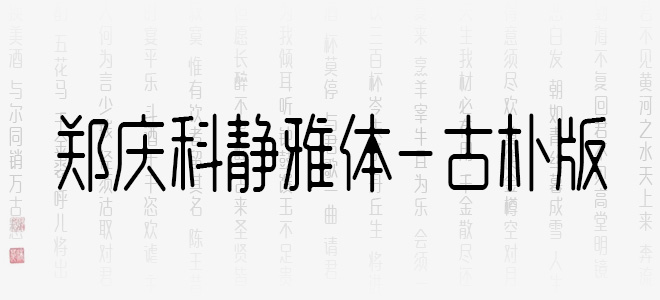
鄭慶科靜雅體-古樸版是一款中文藝術(shù)字體,這款字體是在鄭慶科靜雅體的基礎(chǔ)上演化而成,字體字形和鄭慶科靜雅體-瘦版有些類似,字體都是屬于那種細(xì)細(xì)長長的,該字體包含大陸簡體漢字6763個(gè)、英文大小寫52個(gè),阿拉伯?dāng)?shù)字10個(gè),以及682個(gè)符號(hào),適合應(yīng)用于藝術(shù)設(shè)計(jì)、平面宣傳設(shè)計(jì)、海報(bào)設(shè)計(jì),書法字帖等領(lǐng)域,需要的朋友可以前來本站下載。
鄭慶科靜雅體-古樸版 中文字體